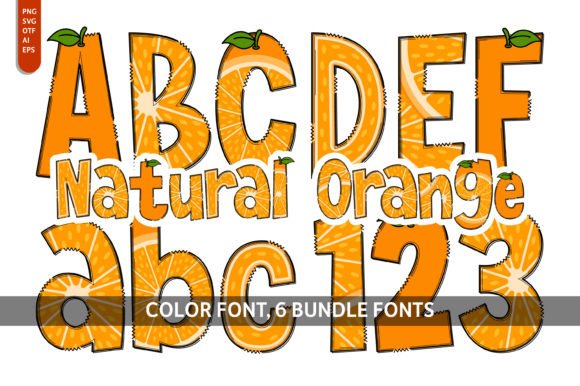
Natural Orange
適切なデザイン要素を見つけるのは難しい場合がありますが、Natural Orangeは作品を即座に引き立てる優れたコレクションを提供します。
POD(オンデマンド印刷)製品、結婚式の招待状、またはソーシャルメディアのグラフィックを作成している場合でも、Natural Orangeは理想的です。